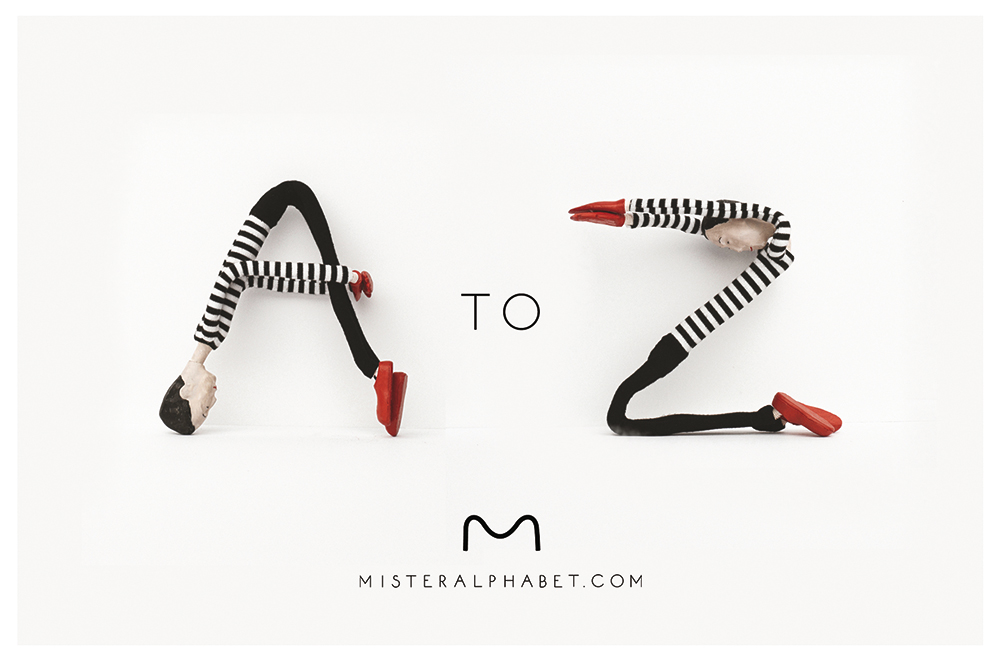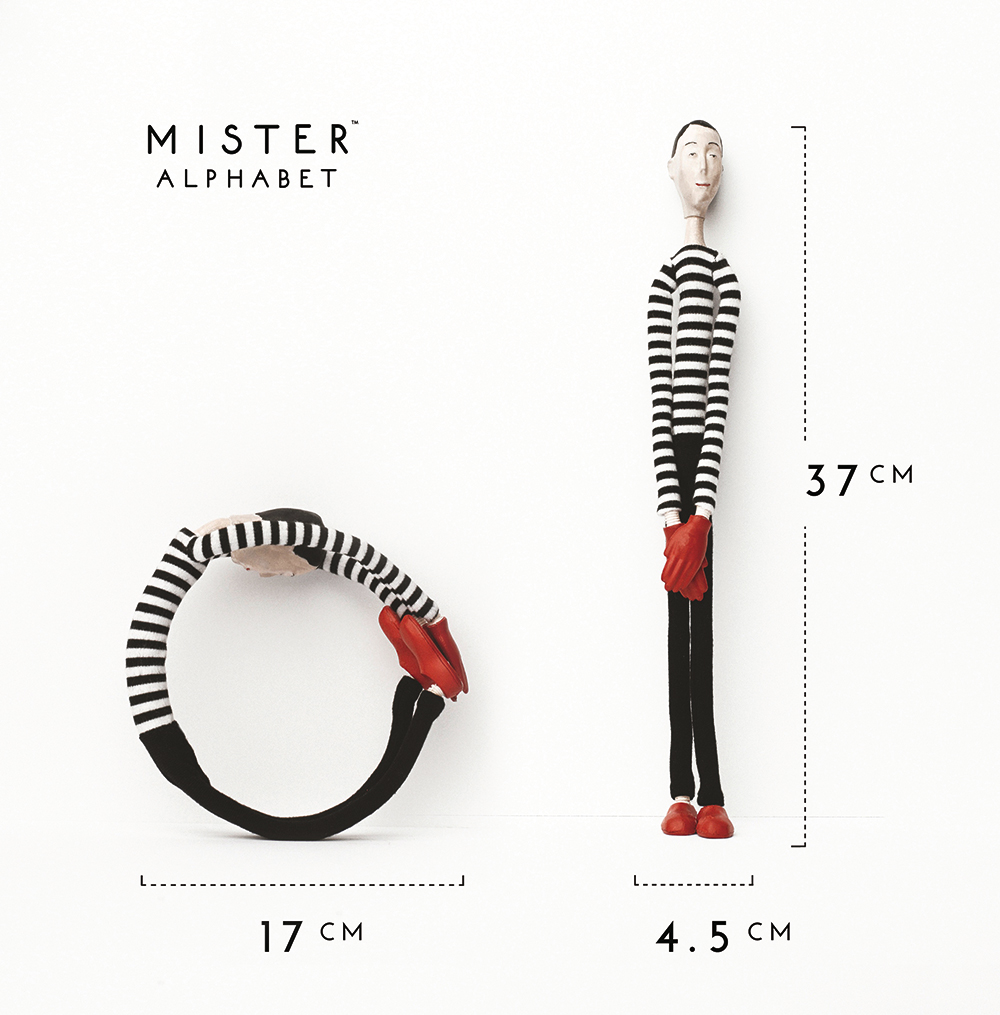
글자소년 : 미스터 알파벳 프로젝트
미스터 알파벳은 구부려서 알파벳의 모든 글자를 만들 수 있도록 디자인된 작은 입상이다. 로스앤젤레스의 마샬과 헤일리 로우만이 형상과 글자 형태의 혁신적 상호작용을 통해 알파벳에 생명을 불어넣은 것이다. 이로써 성인과 아동을 한데 모았고 디자인과 교육도 한데 모았다.
미스터 알파벳
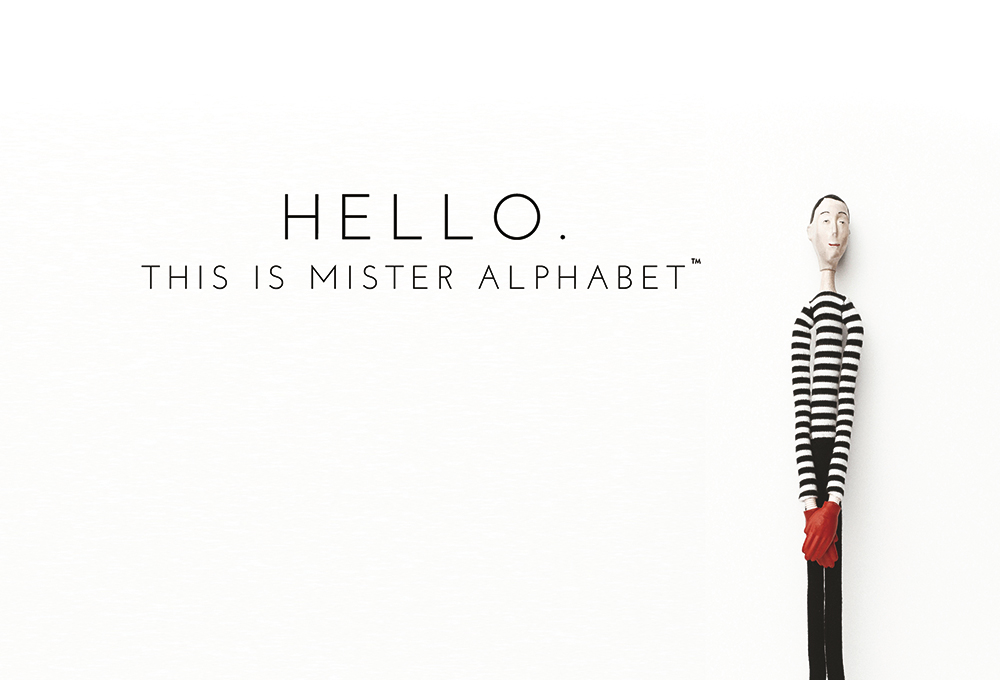
“예술과 패션에서 우리가 한 체험들로부터 영감을 받아 미스터 알파벳을 만들었고, 이는 우리가 디자인, 교육, 공동체에 대해 공유한 열정을 대변하는 존재입니다. 우리는 석고조각 같은 미소를 보이며 눈이 왕방울만한 인형을 만들려고 한 게 아니라, 눈에 띄는 아이콘적인 배색을 하여 보다 평온한 느낌의 것을 보이고 싶었습니다. 어떤 사람들은 우리의 입상이 프랑스의 어릿광대 같다고 이야기하지만 우리의 첫 프로토타입은 ‘프랑스’보다는 ‘팀 버튼’을 더 닮아 있었습니다.”
마샬이 설명한다.
그 첫 번째 프로토타입은 꽃 같은 철사, 지혈대, 구운 점토, 천, 전자 테이프 등으로 만들어졌으며, 프로덕션 모델에서는 머리 이외 부분에 손으로 빚은 디테일들을 많이 살려냈다. 이후 결국엔 CAD로 이행해야 했다. 헤일리가 덧붙인다.
“손과 발에 있는 자석은 글자들의 형성을 돕는 것으로 디자인되었습니다. 하지만 또한 금속 표면에서 다양한 방식으로 매달릴 수도 있게 하고요.”
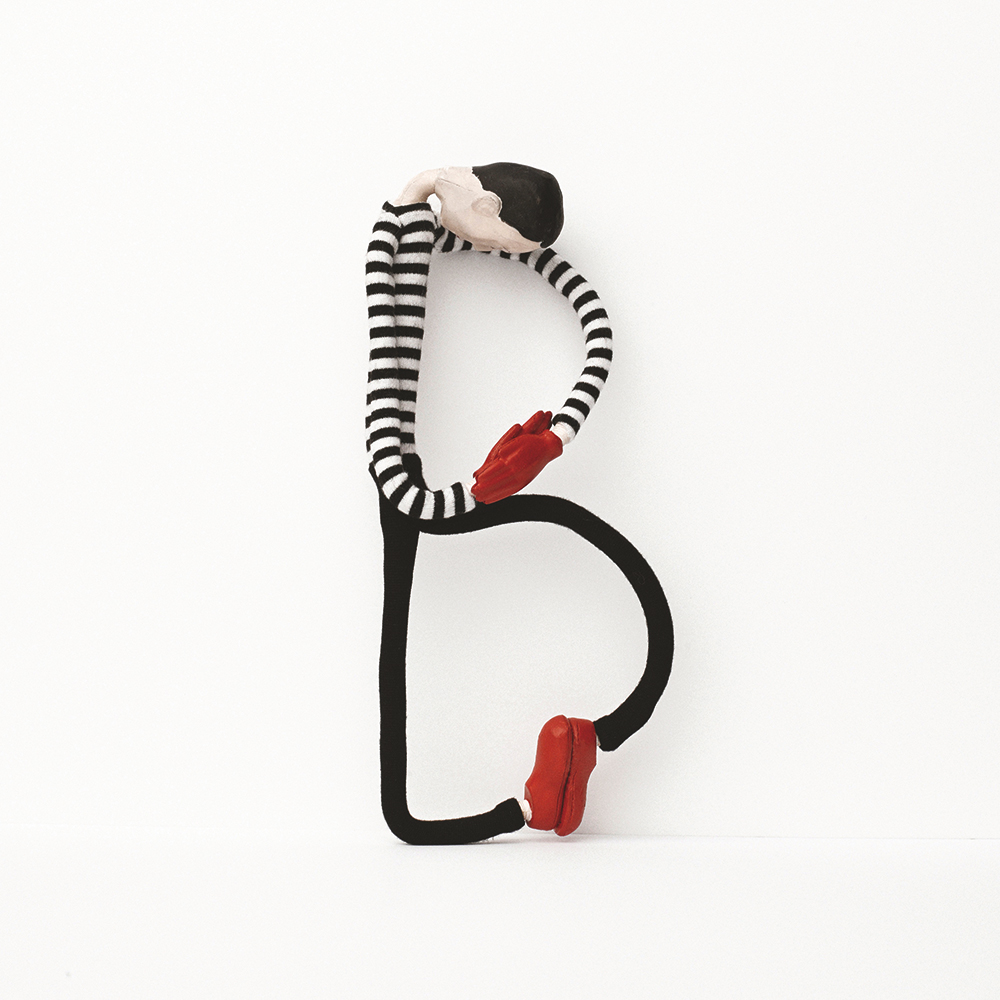
법이 규정한 24개의 모든 기계적 안전성 평가를 성공적으로 통과해 큰 지원을 얻어낸 이 프로젝트는 올해 첫 생산을 앞두고 있다.
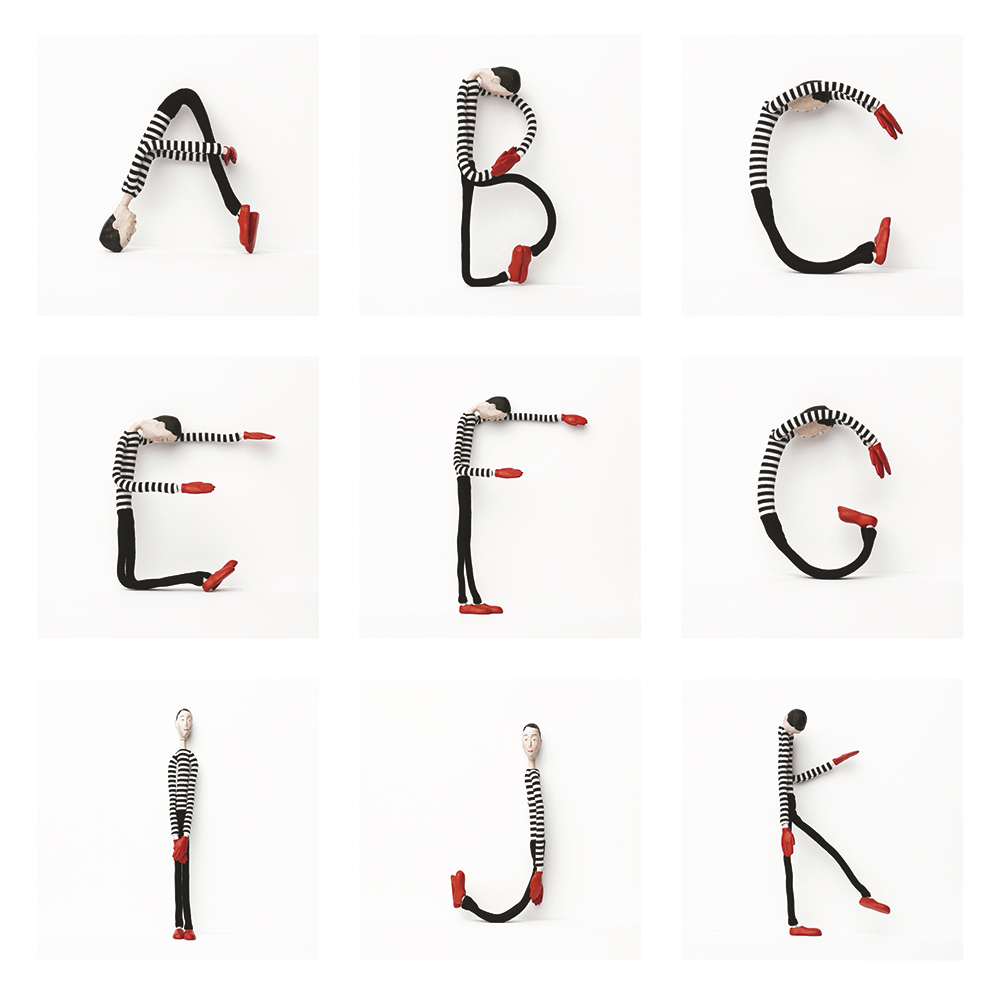
Project by 마샬과 헤일리 로우만(MARSHALL & HALEY ROEMAN)